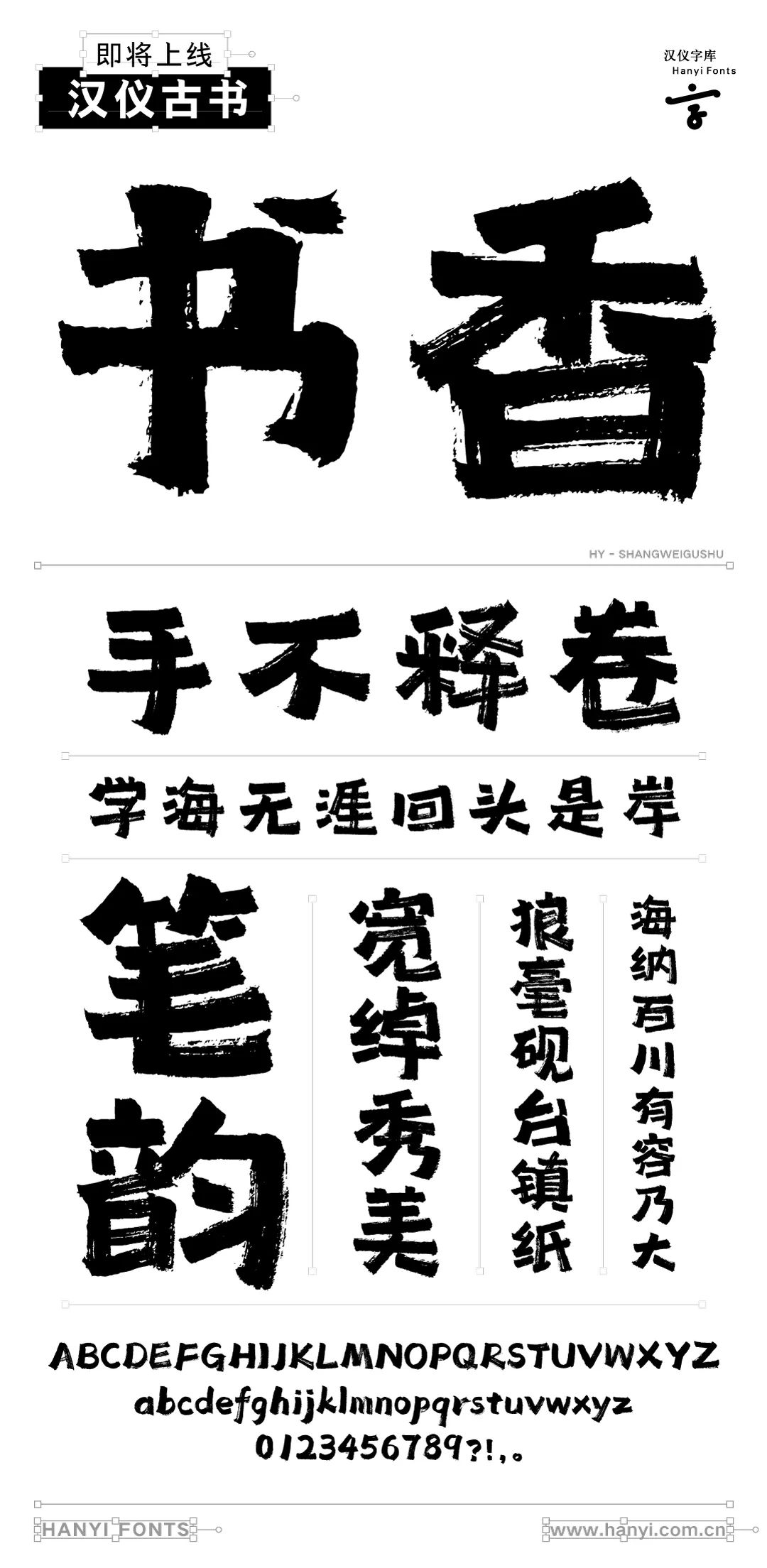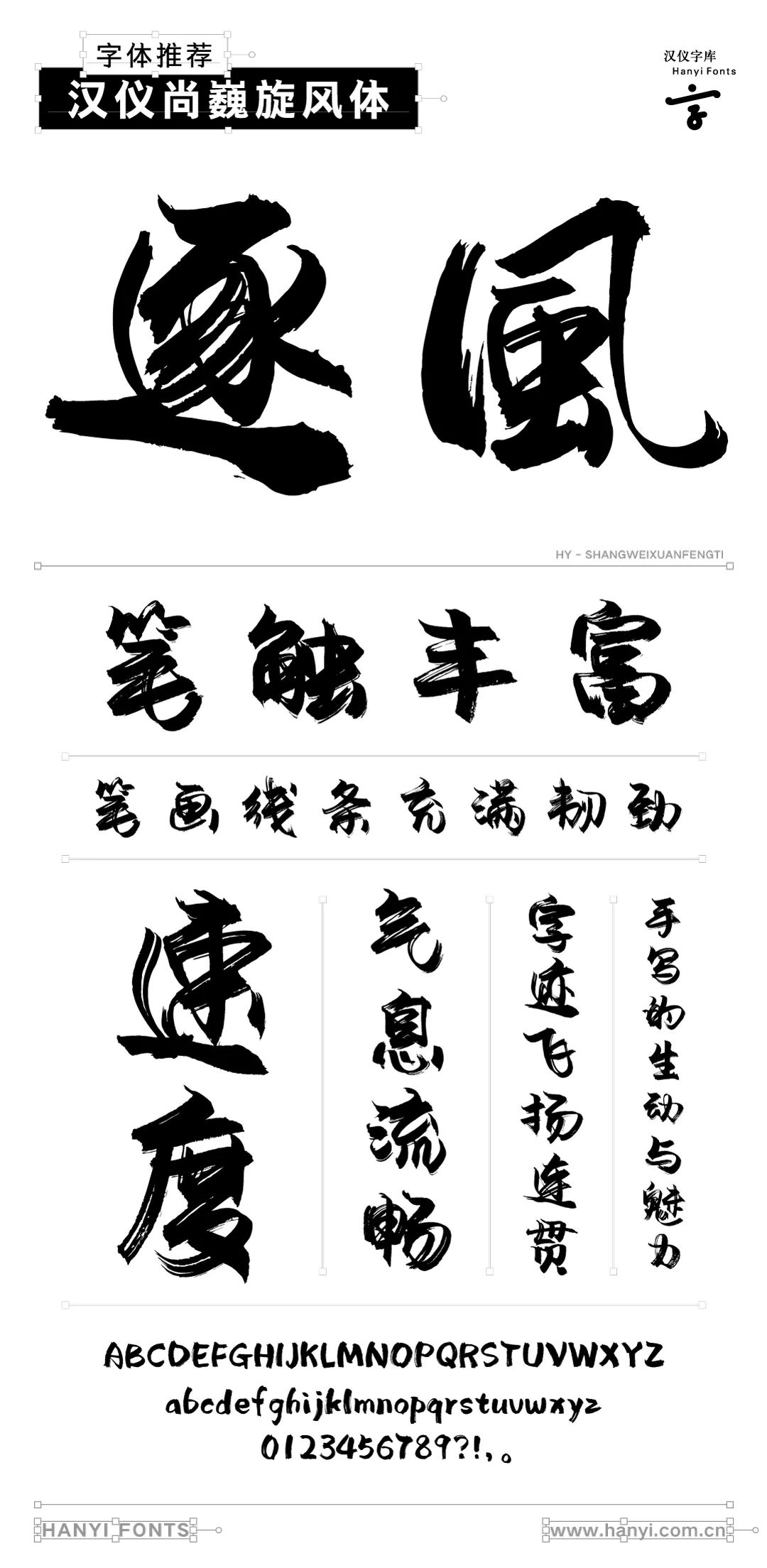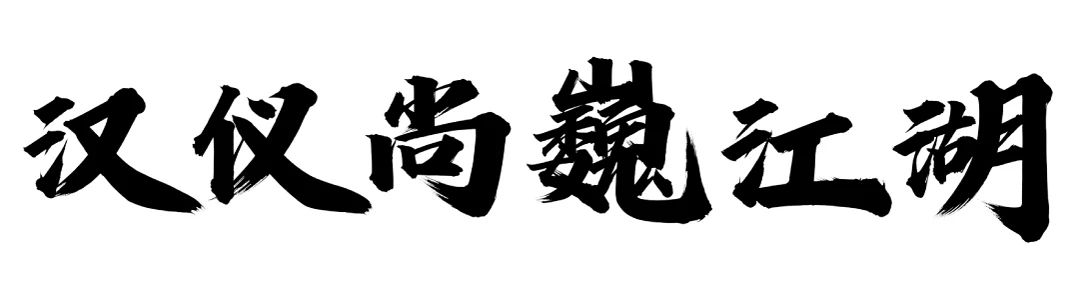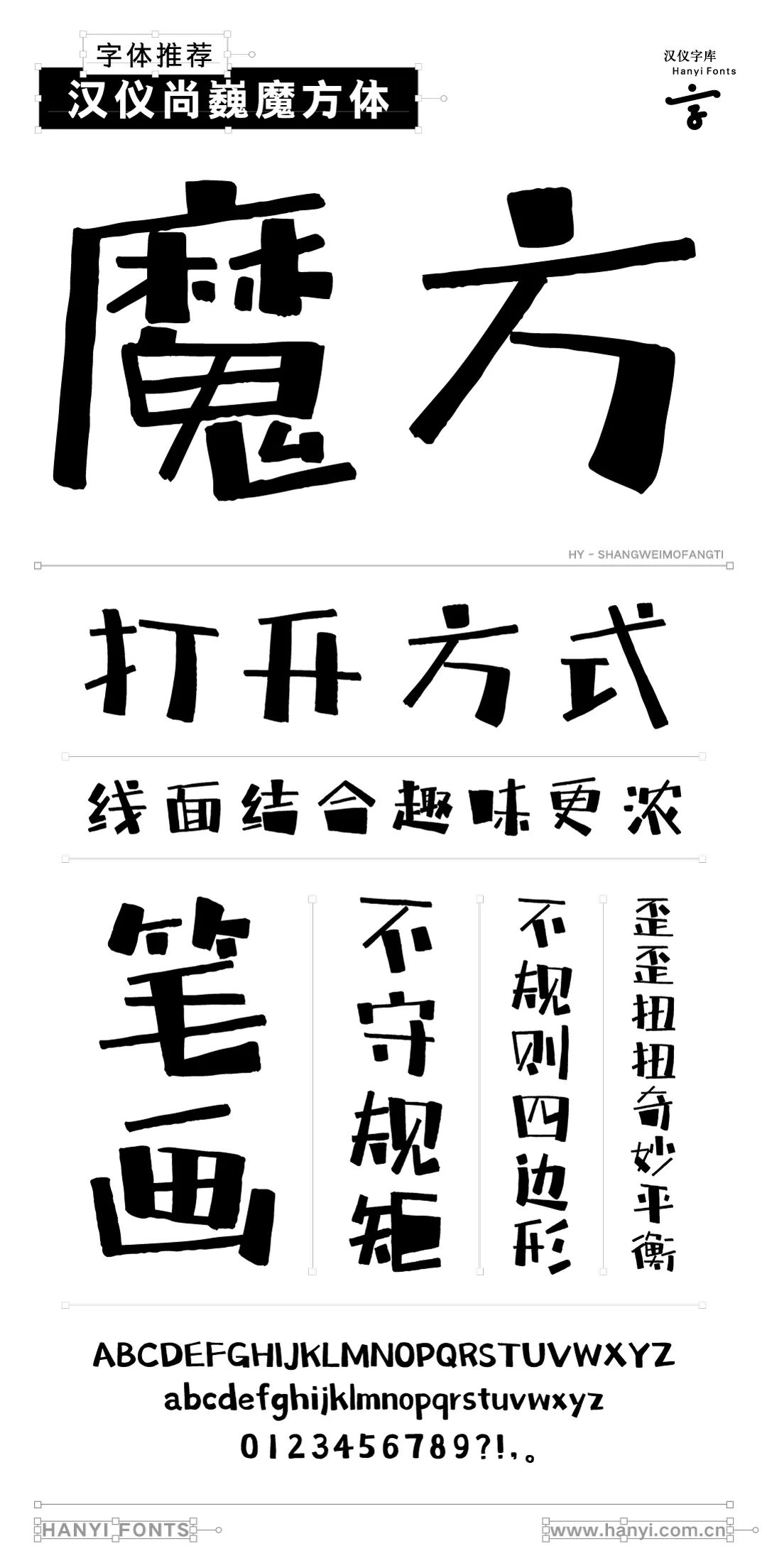
震惊,,,著名字体设计师尚巍老师因车祸去世
今日从微信公众号笔染时光得知,著名字体设计师尚巍老师因车祸去世,表示震惊和惋惜。
尚巍老师是著名的字体设计师,曾为《我不是药神》《悟空传》《快乐大本营》《军师联盟》等影视作品片名及字幕、中国劲酒等知名品牌进行字体创作。
五岁开始练字,
期间兜兜转转做过很多事,
最后又兜兜转转回到了手写行业,
开始懂得坚持,
开始想要做极致。
很多人问我为什么这么多年还在不停写字?
其实坚持手写至今是因为:
我觉得笔呈现在纸张上面的文字远比屏幕上的有份量。
——书写人 尚巍
尚巍或者尚巍工作室和汉仪字库合作出品众多知名的字体字库,比如:汉仪尚巍荒野 W、汉仪尚巍花语 W、汉仪尚巍自由 W、汉仪尚巍稚拙 W、汉仪尚巍和风体 W、汉仪尚巍小顽童 W、汉仪尚巍旋风体 W、汉仪尚巍魔法体家族、汉仪尚巍魔方体W、汉仪尚巍少年体W、汉仪尚巍流云体W、汉仪尚巍小时候W、汉仪尚巍清茶体W、汉仪尚巍手书W、汉仪尚巍顽皮黑 W、汉仪尚巍砂糖桔 W、汉仪尚巍朴拙 W、汉仪尚巍古书 W
其中比较著名的就是尚巍手书的书法字体
汉仪公众号了解到,尚巍签约了汉仪字库独立设计师,目前还在进行的几款字体还未发布。
尚巍
汉仪字库签约手写人,独立设计师
从2016年,汉仪发布了尚巍的第一套字体汉仪尚巍手书开始,以尚巍为标签的,一个张扬的,醒目的,全新的字体面貌,迅速铺满了大街小巷。有关汉仪尚巍手书的争论,至今犹在。
在这将近五年的时间里,尚巍陆续完成了汉仪尚巍清茶体、汉仪尚巍少年体、汉仪尚巍魔法体、汉仪尚巍魔方体、汉仪尚巍自由、汉仪尚巍荒野、汉仪尚巍小时候、汉仪尚巍花语、汉仪尚巍稚拙、汉仪尚巍朴拙以及工作室产品汉仪笔染润书等等···包括未完成的,已有20余套。他用他看似执拗又野蛮的方式,闯荡在自己的江湖,并努力用自己的一件件作品回馈给支持他的人们。
今天除了汉仪尚巍江湖即将上线以外,汉姨还带来了另外两款即将上线的作品,以及几款深受大家喜爱的作品。不要满足的太早,一起期待尚巍更多的下一套。
汉仪尚巍古书
推荐汉仪尚巍魔方体
字体推荐汉仪尚巍旋风体
字体推荐汉仪尚巍自由体
尚巍老师的离去,是对字体界重大打击,愿尚老师在天国微笑前行。
逝者安息,生者如斯。